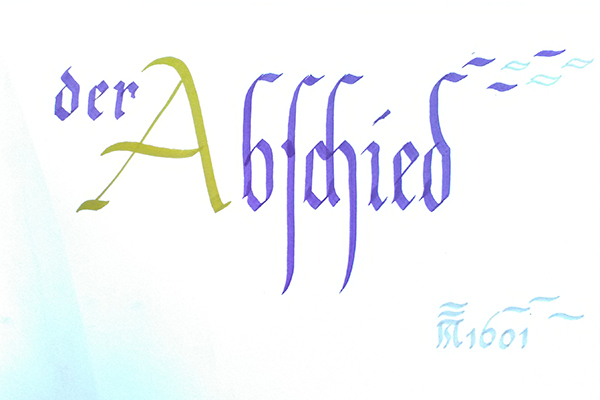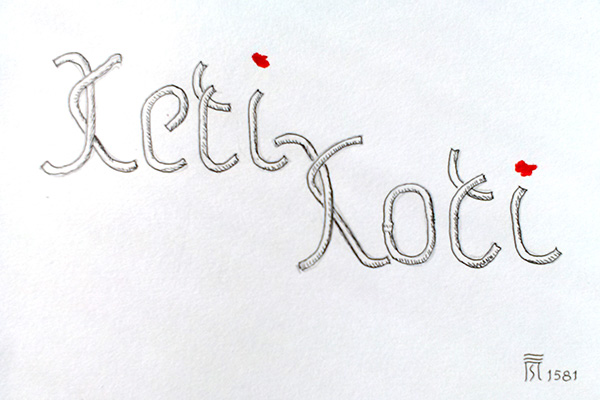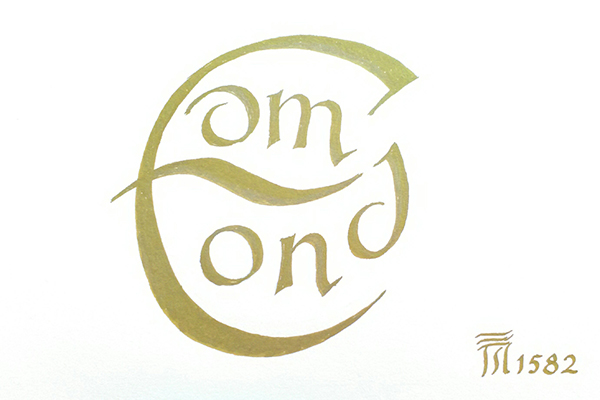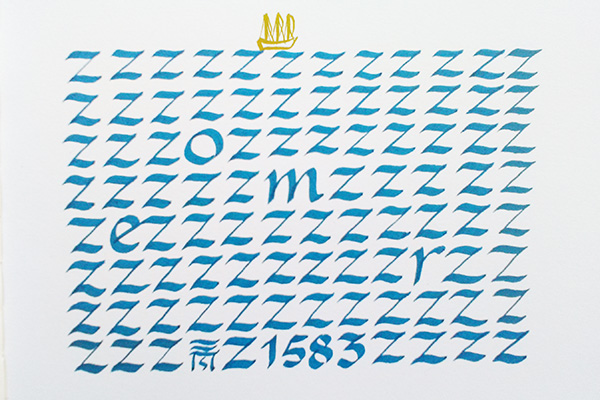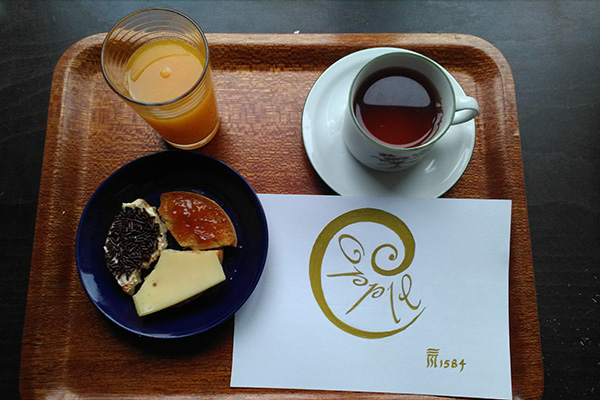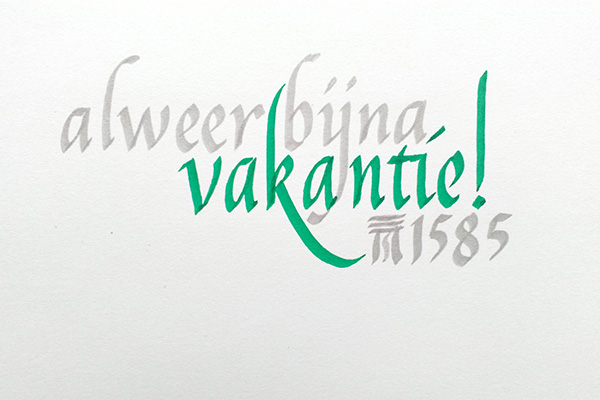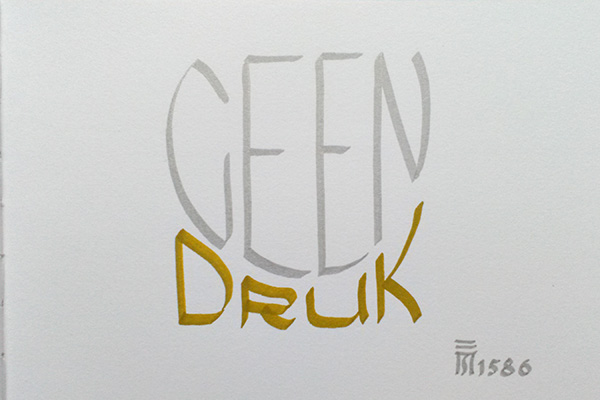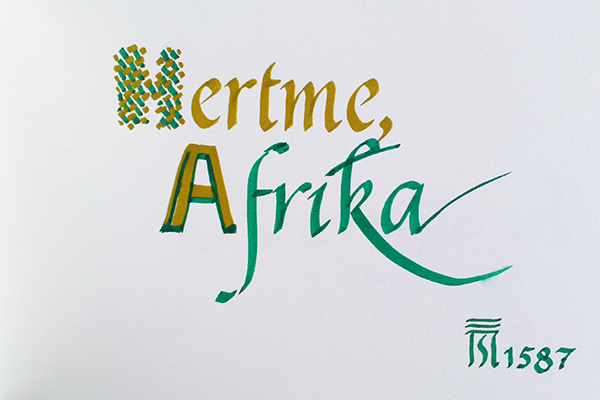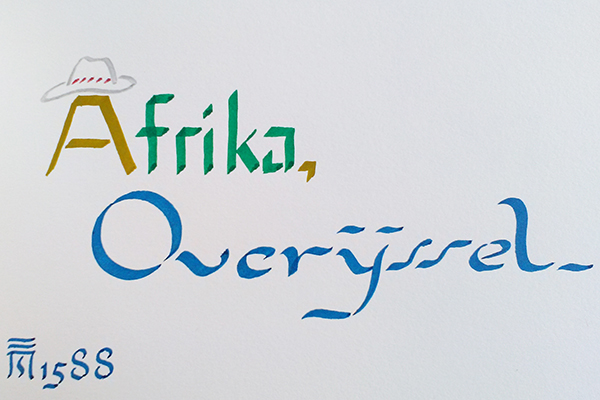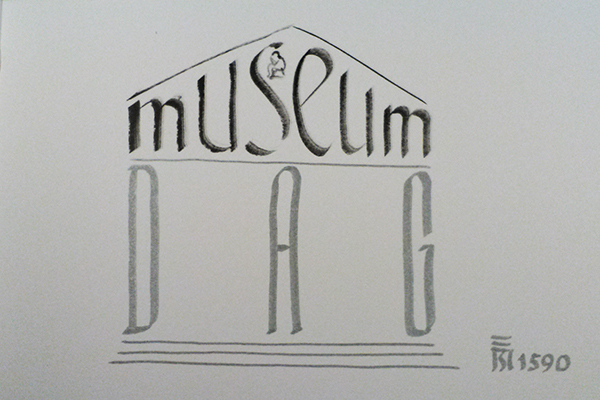
**) Since 24 february 2014, I have been producing one calligraphic scribble each morning before breakfast, as an exercise, as well as a greeting card from time to time, sent to friends and acquaintances. This page shows the results of this project, and of my attempts to meet my self- imposed schedule for birthday cards and such. Sinds 24 februari 2014 maak ik elke ochtend vóór het ontbijt een kalligrafische krabbel. Deze pagina laat de resultaten van dit project zien, en mijn productie aan kaarten: verjaardagskaarten en dergelijke, en verder van tijd tot tijd een wenskaart voor vrienden en kennissen.
BB1598 Corries docent was gisteravond bijna geheel stemloos
BB1597 Gisteren verplicht groot gedrukt met (ongeveer) Yves Klein International Blue.
Groot vel papier als tafelkleed ingezet om het blauw weer te “vernietigen”
BB1596 Gisteren aardappeldruk gebruikt. Of dat experimenteel was weet ik niet, maar voor mij was het best nieuw.
BB1595 Sarah's introductie verwees naar Yves Klein, maar dan in het klein: ze drukte alleen haar dijbeen af.
BB1593 Goed restaurant in Nunspeet
BB1586 no pressure, not until next week!
BB1586 volgende week pas!
BB1582 happy birthday, brother!
BB1582 een fijne verjaardag, broer!